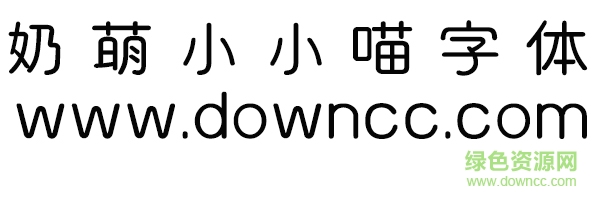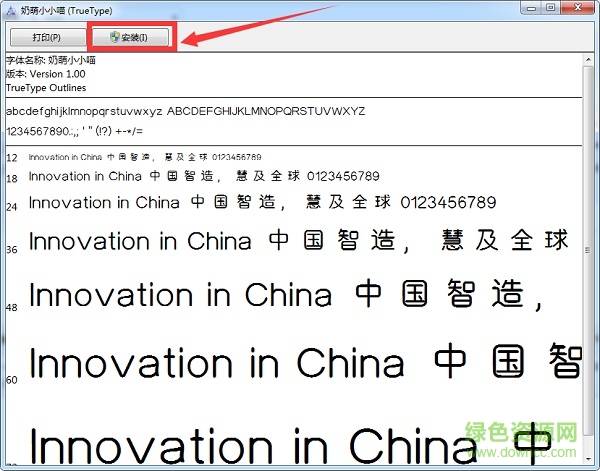
義啟奶萌小小喵字體
奶萌小小喵字體ttf義啟字體推出的免費(fèi)字體資源。小編推薦的這款字體不僅美觀,字體規(guī)范,可使用它設(shè)計(jì)logo、廣告、海報(bào)等等。在電腦上安裝后就可以打開ps等軟件使用了!
義啟奶萌小小喵字體預(yù)覽圖:
奶萌小小喵ttf字體是一款由義啟字庫(kù)全新打造的藝術(shù)字體,該字體讓人第一眼看上去就有一種小奶萌小可愛的想法,小奶萌,小可愛,小迷你,小小喵,整體的字體風(fēng)格就是一種萌萌噠!喜歡的用戶快來綠色資源網(wǎng)下載吧。